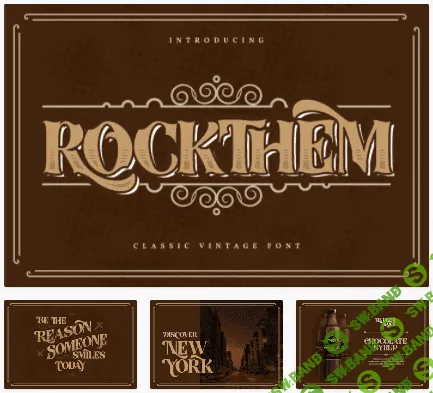
Название: Rockthem Classic Vintage Font (2021)
[elements.envato] Rockthem Classic Vintage Font (2021)
Rockthem | Классический винтажный шрифт в каллиграфическом стиле, такой красивый на приглашениях, таких как поздравительные открытки, фирменные материалы, визитные карточки, цитаты, плакаты и многое другое!